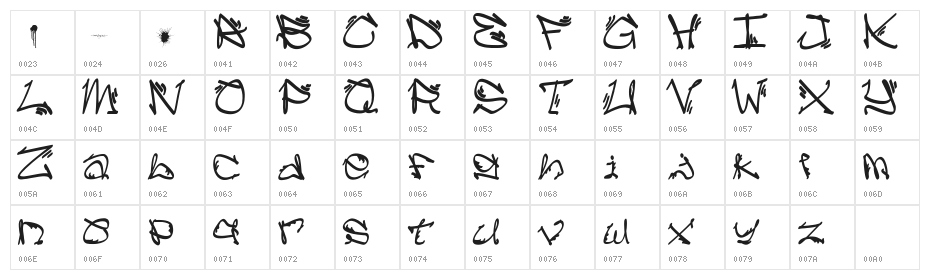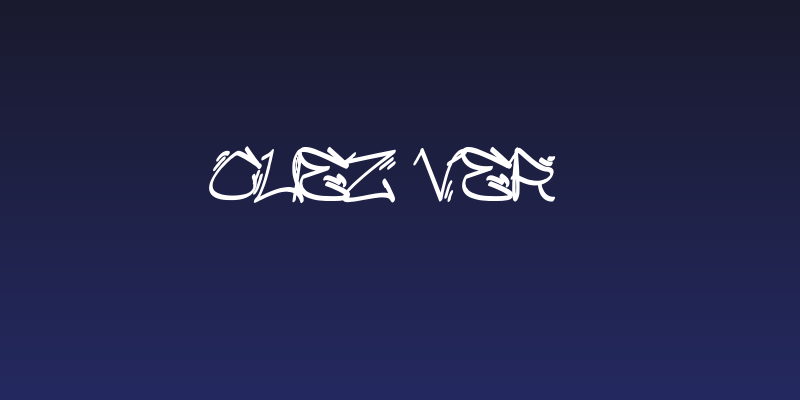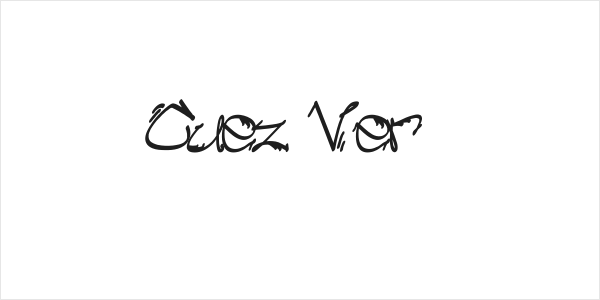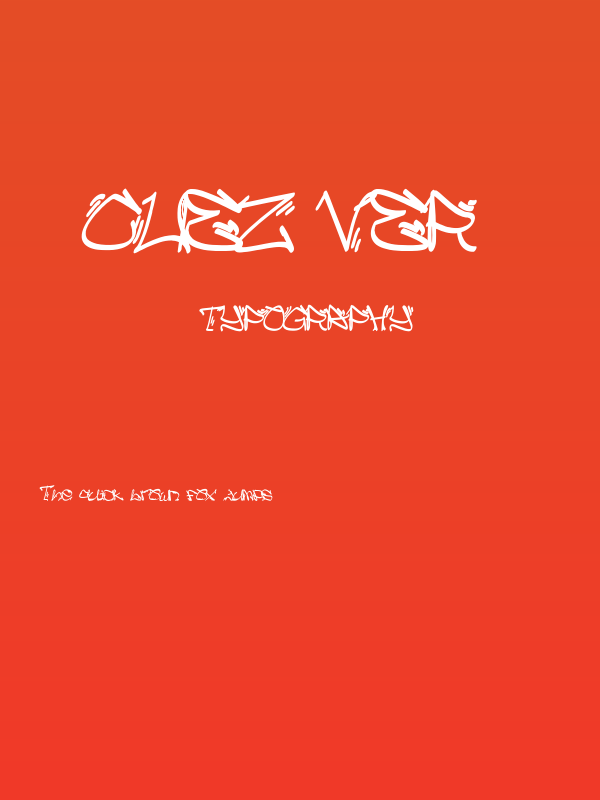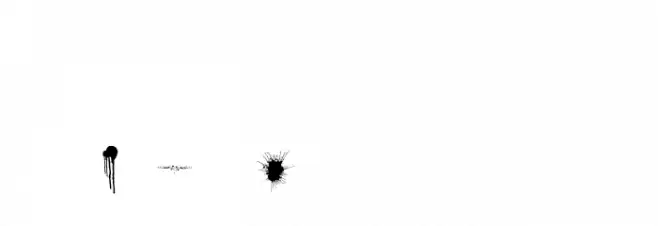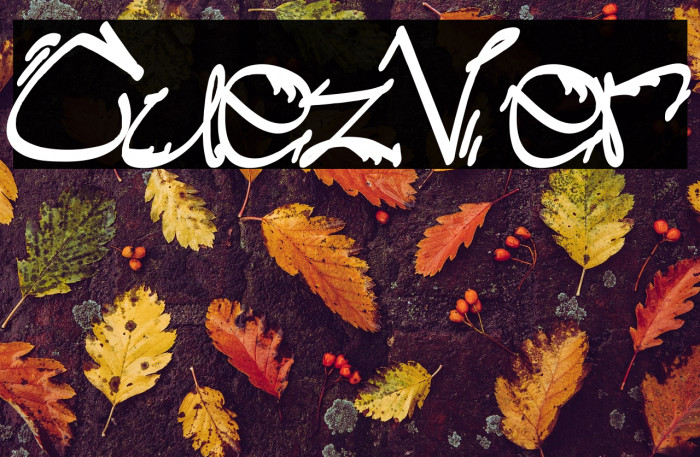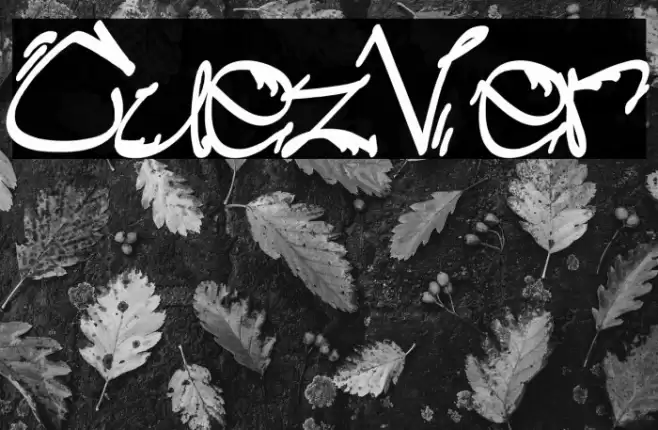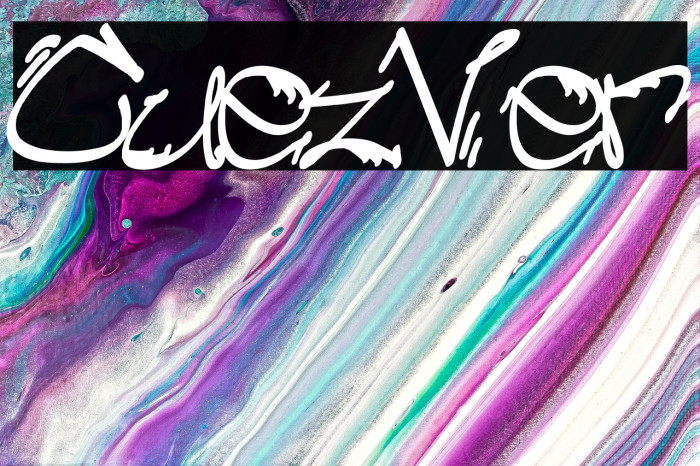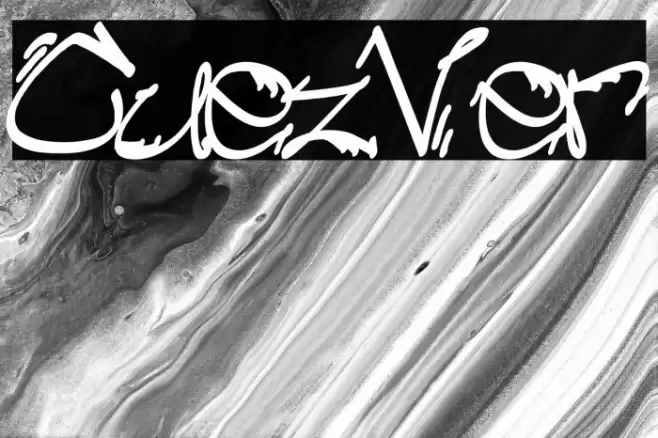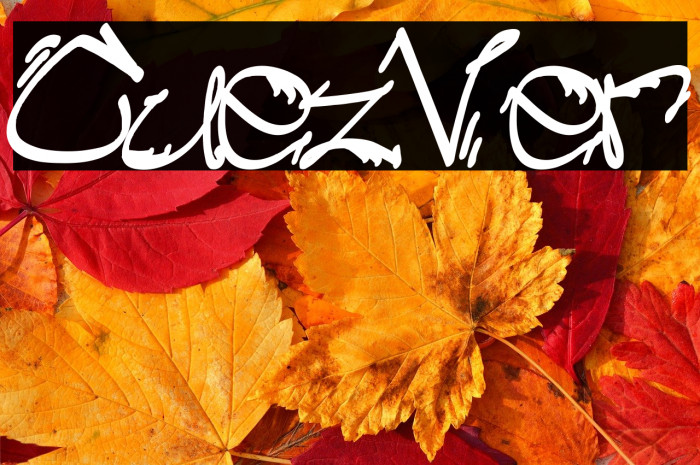
Cuez_Ver3 Font
✎ Graffiti
| Categorii | Graffiti |
| Stil general | Modern, Urban |
| Caz de utilizare | Logos, Posters, Headlines |
| Proiecte propuse | Ideal for street art designs, urban-themed posters, album covers, and edgy branding projects. |